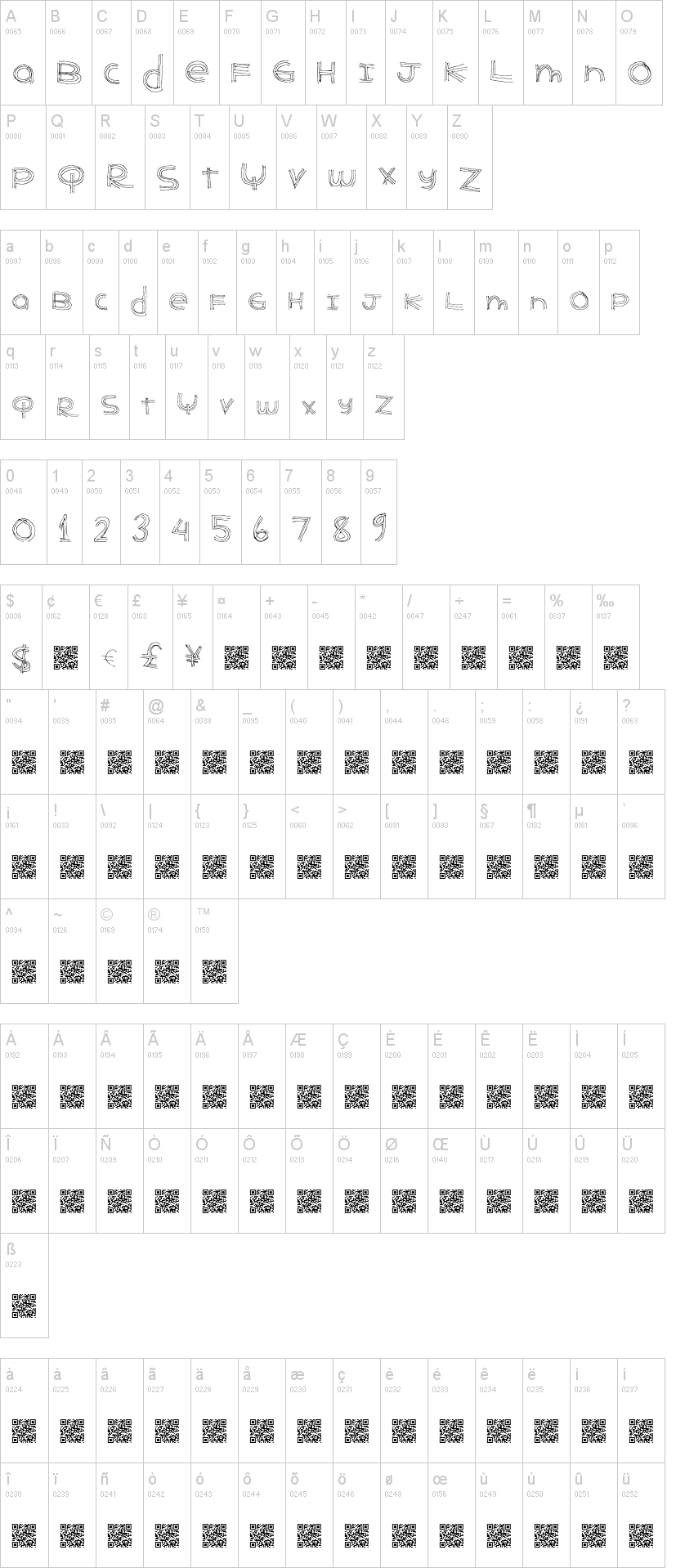
Bender Lines
Bender Lines 字体是一种装饰性的字体,它的字母和数字都被设计成了无限循环的线条。它的设计灵感来自于机器人动画片 Futurama 中的一个主要角色 Bender,这个字体与 Futurama 的主题和风格相符。 Bender Lines 字体的线条笔直而又呈现出一种现代感和科技感。它适用于许多设计项目,例如标志、海报、广告、包装等等。由于其装饰性质,它也可以用于艺术项目或其他需要独特字体的设计中。 总的来说,Bender Lines 字体是一款非常有趣和独特的字体,适合那些想要在设计中体现出科技感和现代感的人使用。
Bender Lines是一款非常不错的手写艺术字体,具有很好的视觉感,适合于文化类的宣传设计、商业类品牌的广告和产品包装设计以及个性化文字排版等较多场景。
Bender Lines字符映射图